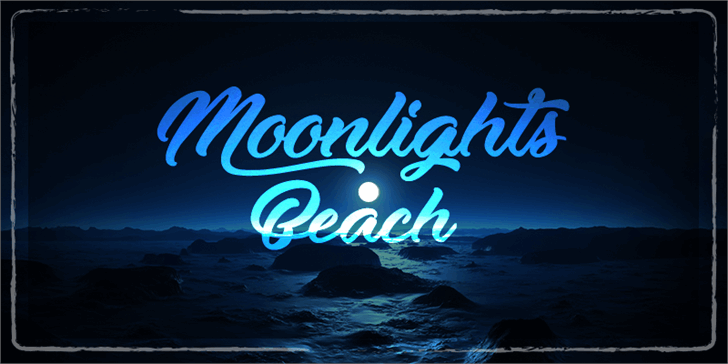
Descubra a paz dos atardeceres em nossa página dedicada à fonte ‘Moonlights on the Beach’. Ideal para criações que transportam seus espectadores através de sensações tranquilas e poéticas, esta fonte criada pela Octotype oferece uma experiência única. Com seu design leve e fluido, você pode trazer um toque único e sofisticado a qualquer projeto, seja em layout editorial ou criação gráfica digital. Não perca tempo: o link para o download da Full Font e sua licença comercial estão à sua disposição no email . Navegue pela tranquilidade dos atardeceres na praia através de uma fonte que captura a essência dessa experiência única.
Designer: Octotype